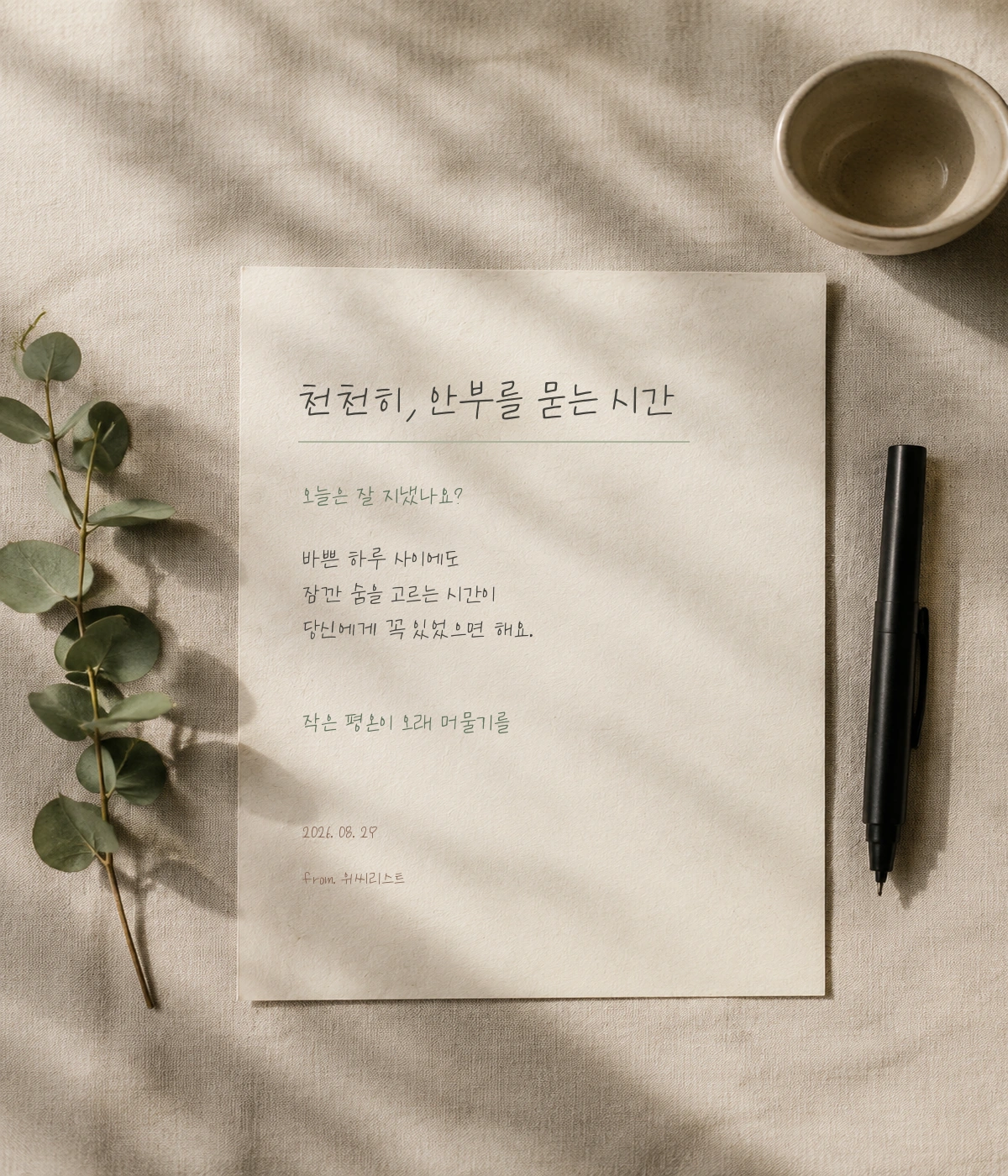
온글잎 위씨리스트 — 온글잎에서 배포하는 무료 폰트입니다. 얇은 펜으로 차분하게 써 내려간 듯한 자연스러운 손글씨체
온글잎에서 2022년에 나온 손글씨 서체입니다. 글씨 주인은 이니셜만 공개돼 있어 알 수 없습니다.
이름을 두고는 조심스럽게 적어야 합니다. 온글잎이 붙인 로마자 이름과 다른 곳에 등록된 이름이 서로 달라서, 위시리스트에서 왔다고 흔히들 짐작하지만 근거가 없습니다. 조형 설명도 없습니다. 디자이너의 한마디라고 붙어 있는 문장은 온글잎이 제공한 기본 문구라, 다른 서체와 글자 하나까지 똑같습니다.
그래서 형태는 파일을 보고 적습니다. 온글잎 여섯 종 가운데 획이 가장 가늘어 자면을 채우는 비율이 낮고, 낱자는 정사각형에 가깝습니다. 펜으로 흘려 쓴 인상이라 다른 다섯 종의 동글동글한 느낌과는 결이 다릅니다.
굵기는 하나이고 현대 한글 11,172자를 모두 담아 어떤 글자를 넣어도 빠지지 않습니다. 획이 가는 만큼 작은 크기나 어두운 배경에서는 묻히기 쉬우니 크게 쓰세요. 상업적으로 쓸 수 있지만 폰트 수정은 금지됩니다.